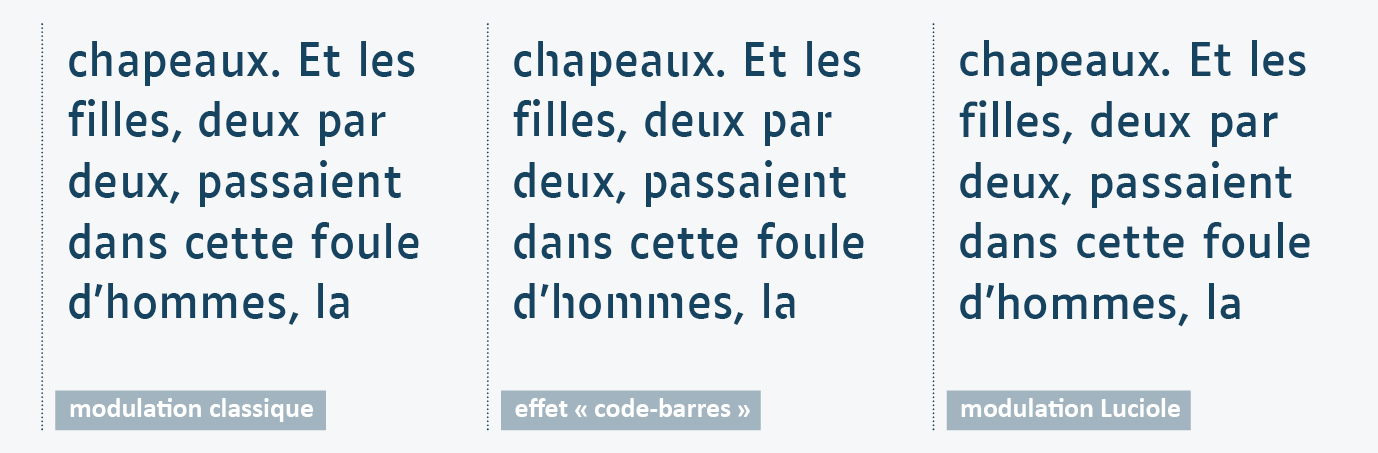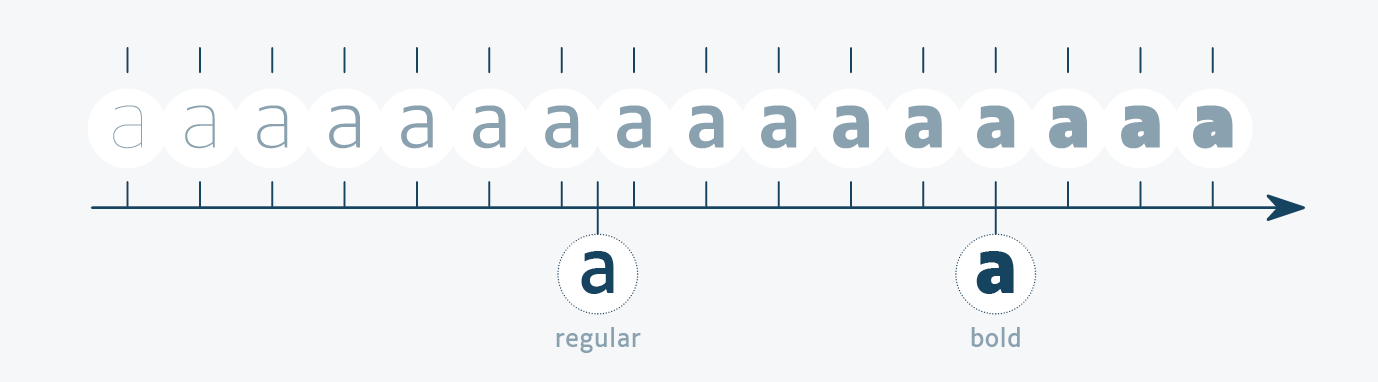
Le projet Luciole a débuté il y a un peu plus de six ans, pour répondre au besoin d’améliorer l’accessibilité des documents scolaires proposés aux jeunes élèves déficients visuels.
Une équipe pluridisciplinaire s’est constituée, avec pour objectif la création d’un caractère typographique conçu spécifiquement pour les lecteurs malvoyants. Pour définir les critères
de design de ce caractère, nous avons croisé trois champs de compétences :
• le versant médical (médecin ophtalmologiste, orthoptiste, psychologue) ;
• le versant de l’édition adaptée (transcripteur spécialisé, directrice de service de transcription) ;
• le versant typographique (dessinateur de caractères, développeur technique).
Il s’agissait non seulement de faire évoluer des habitudes ancrées depuis longtemps dans
le domaine de la déficience visuelle, mais aussi d’apporter une réponse concrète, en mettant à disposition un caractère
conçu pour les professionnels de l’édition adaptée.
Quatre ans après sa sortie, le caractère Luciole s’est affirmé comme un nouveau standard typographique dans le domaine de la déficience visuelle en France.
Il est utilisé par des éditeurs spécialisés, des transcripteurs, des enseignants spécialisés, des développeurs.
Nous souhaitions revenir en détail sur les critères
de sa conception et les partager au plus grand nombre, pour qu’ils bénéficient aux projets à venir dans le champ de la déficience visuelle.
Les professionnels en France définissent généralement la déficience visuelle par 2 critères :
• une acuité visuelle (AV) inférieure à 3/10 après correction
• et/ou un champ visuel (CV) inférieur à 20°.
La classification de l’OMS retenait également ce critère de l’acuité visuelle inférieure à 3/10 dans sa version de 1972. Elle a évolué vers une définition plus large, on distingue à présent 5 grandes catégories, en simplifiant :
• la déficience visuelle légère (< 5/10)
• la déficience visuelle modérée (< 3/10)
• la déficience visuelle sévère (< 1/10)
• la cécité (< 1/20) et la cécité totale (pas de perception)
• la déficience de la vision de près.
Selon cette dernière classification, les personnes avec une déficience visuelle représentent environ 1,7 million de lecteurs en France. En pratique, c’est surtout l’acuité de près qui déterminera les besoins en termes de lecture. Une déficience visuelle peut avoir un impact différent selon qu’elle est congénitale ou acquise, précoce ou tardive, isolée ou associée à d’autres troubles ou pathologies.
Nous avons défini deux types de critères : des critères d’usage et des critères de design.
Les critères d’usage sont au nombre de 3 : un caractère qui soit gratuit, avec une licence connue (Creative Commons),
et simple d’utilisation (contient les 4 variantes stylistiques de base).
Les critères de design sont au nombre de 12, nous les avons tous représentés ci-dessous
[Figure 1] pour plus de clarté : caractère linéale, contreformes ouvertes, interlettrage important, différenciation importante, proportions étroites, diacritiques
accentués, faible modulation, épaisseur importante, variante
de graisse contrastée, italique non cursive, casse étendue et cohérence du système. Nous allons développer les 3 critères de design les plus complexes à appréhender : la question des proportions,
celle de la modulation du trait, et celle de l’épaisseur du trait.
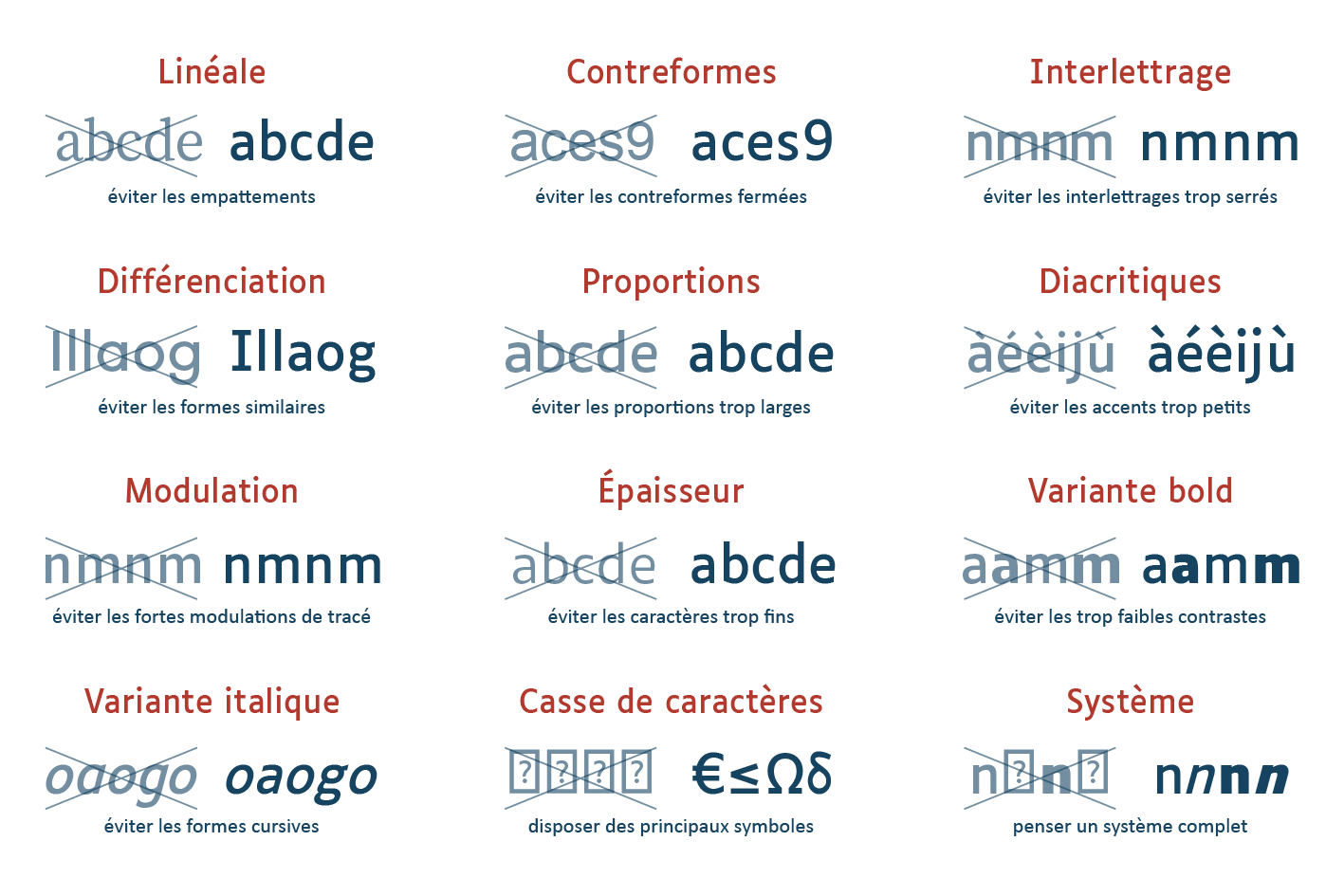
Le corps 20 peut être considéré comme le corps de lecture usuel dans le domaine de la déficience visuelle. En pratique, le corps varie généralement entre 16
et 20 pour l’édition adulte, entre 20 et 24 pour l’édition jeunesse. Les exceptions sont nombreuses, dans le cas d’un champ de vision tubulaire par exemple. Néanmoins,
d’un point de vue du design, il faut considérer que l’usage le plus répandu est celui d’un corps
de lecture près de deux fois supérieur au corps de lecture pour un lecteur clairvoyant.
Cet usage a de nombreux impacts sur les critères de conception, particulièrement
sur celui qui concerne les proportions. L’enjeu est de trouver un équilibre entre un caractère qui soit suffisamment ample pour être lisible, et suffisamment étroit pour que
le nombre de signes à la ligne ne devienne pas trop faible, ce qui constituerait un facteur très important de fatigabilité pour le lecteur [Figure 2].
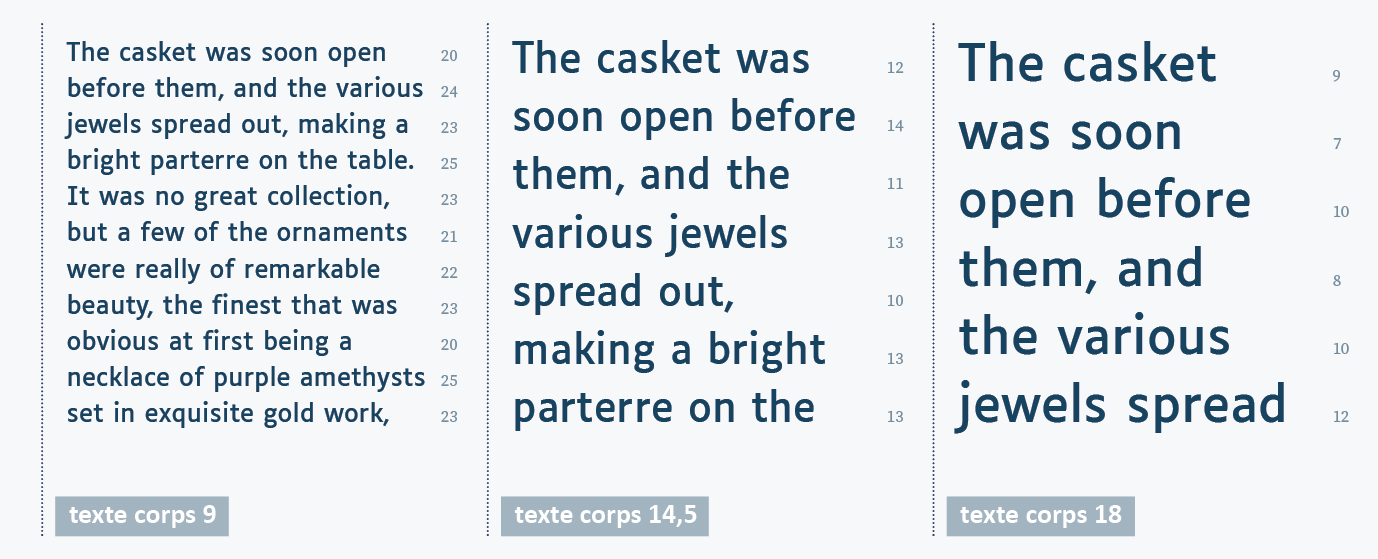
Les lettres du Luciole ont donc des proportions (très) légèrement plus étroites qu’un caractère classique pour augmenter le nombre de signes à la ligne.
D’un point de vue plus global, le dessin n’est pas abordé de la même façon pour un corps 10 ou pour
un corps 20 : le rapport aux corrections optiques par exemple s’en trouve modifié, ainsi que celui à l’intermot.
La question de la modulation du trait est en lien direct avec celle des corrections optiques. De façon classique en typographie, lorsqu’un fût et une courbe se rencontrent,
on observe un fort amincissement de la courbe au point de jonction. L’ampleur de cette modulation du trait varie selon les caractères mais c’est presque une constante